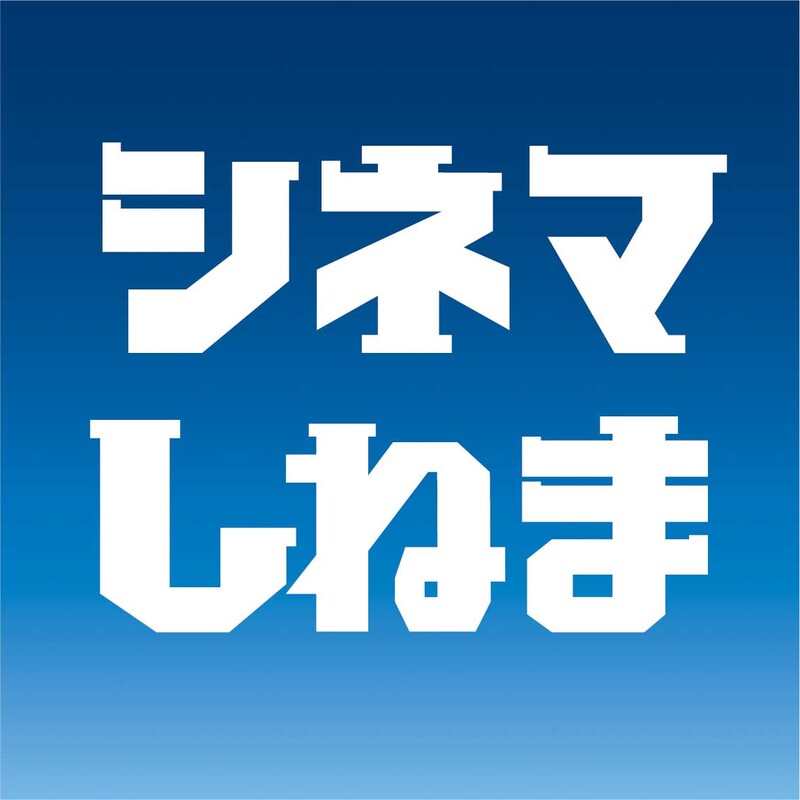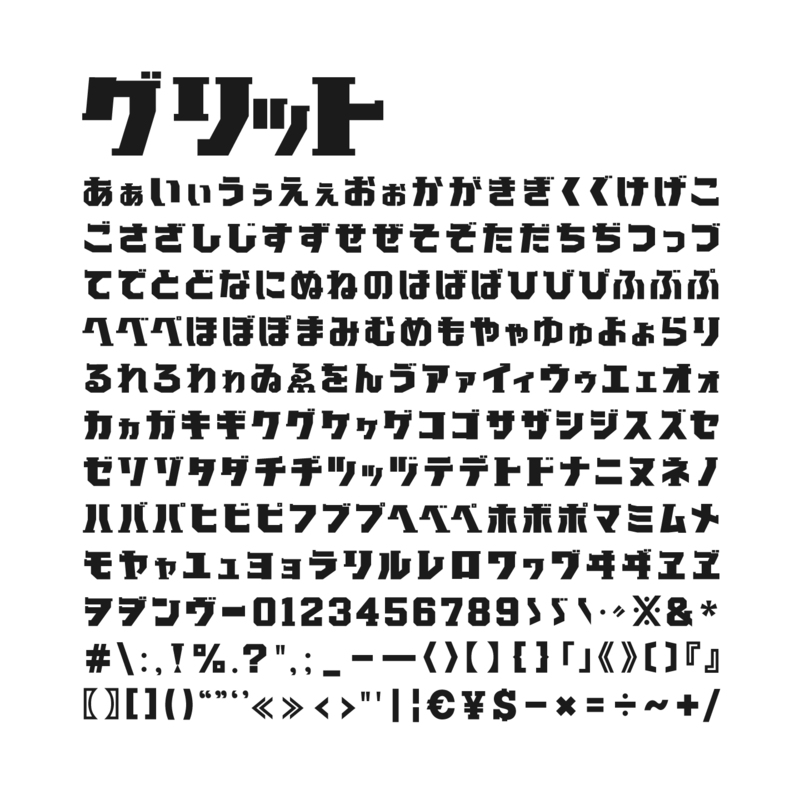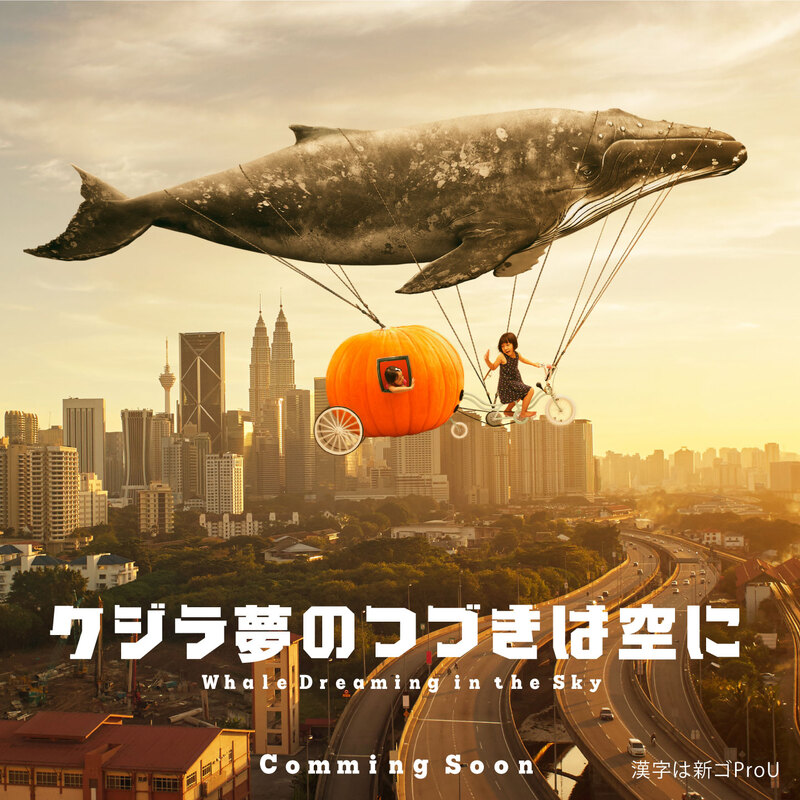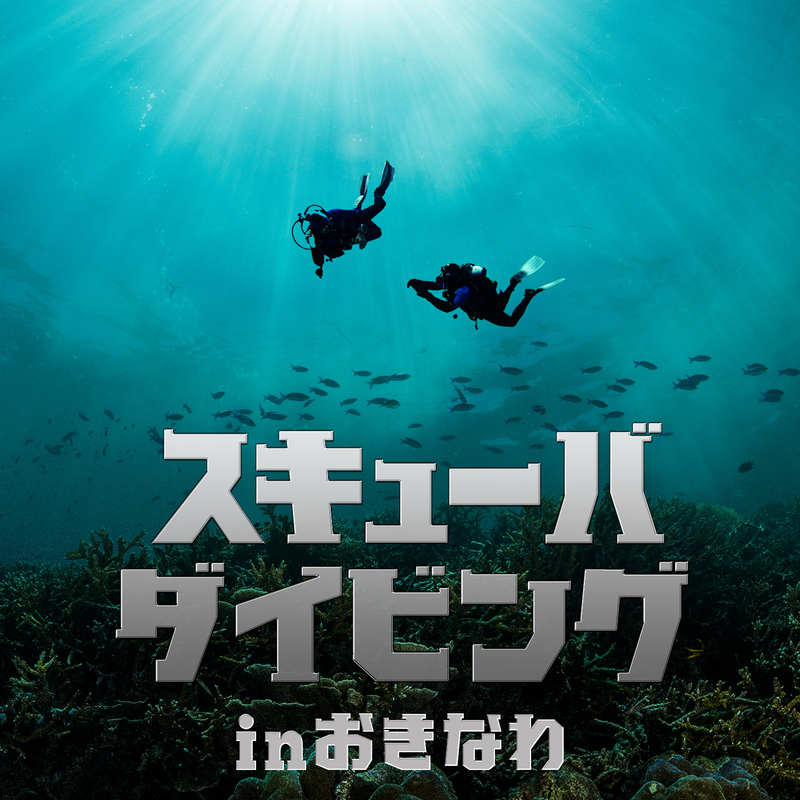
シネマフォント グリット|Chiba Design|和文・欧文・デザイン書体のダウンロード販売|フォントファクトリー
商用利用可能なオリジナルフォントです。アメリカ西部劇をイメージしたヴィンテージなフォント。とめに欧文のセリフにあたる部分を加えてアレンジしました。タイトルロゴ、POPなどの作成に便利です。かな・アルファベット・数字・約物。アウトライン抽出可。
シネマフォント グリット